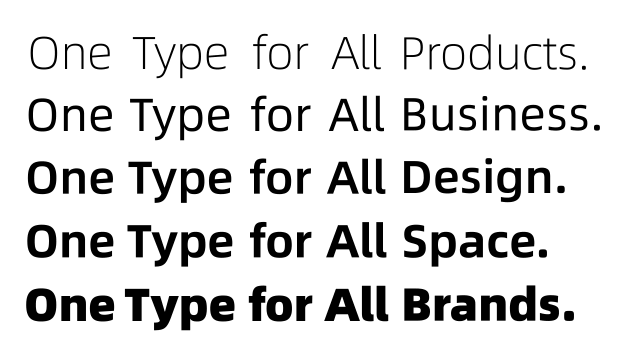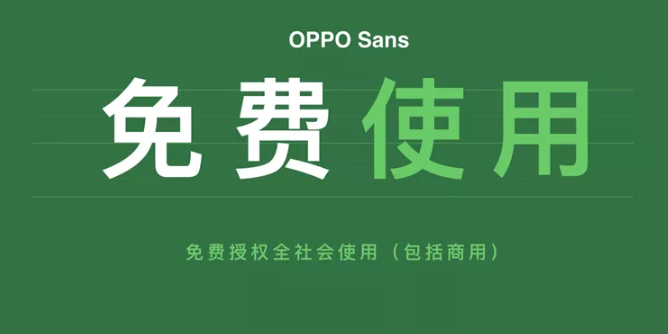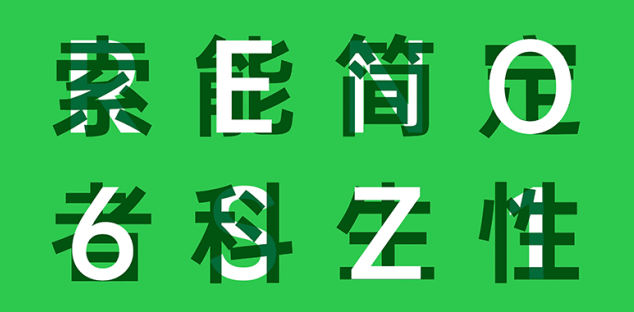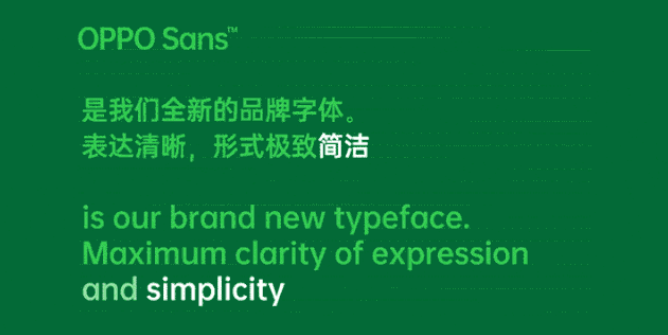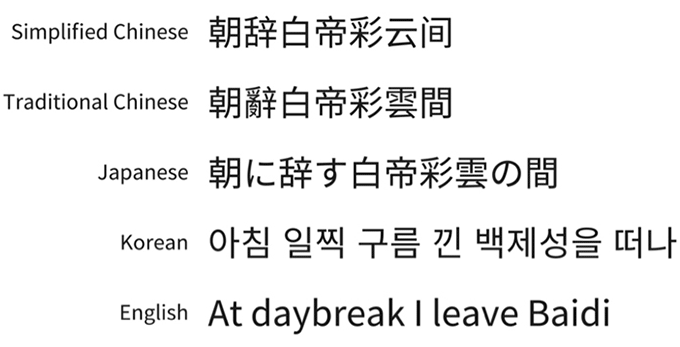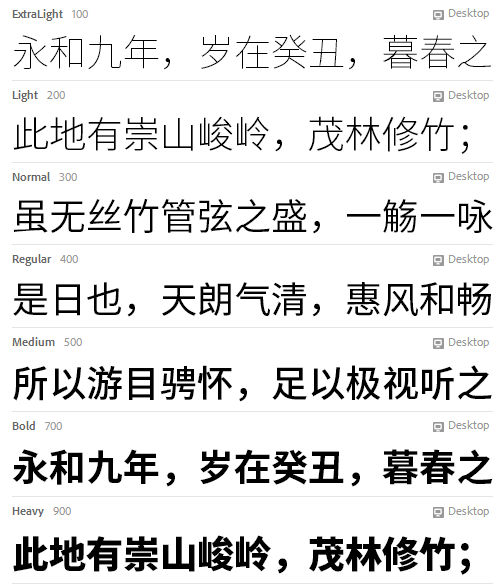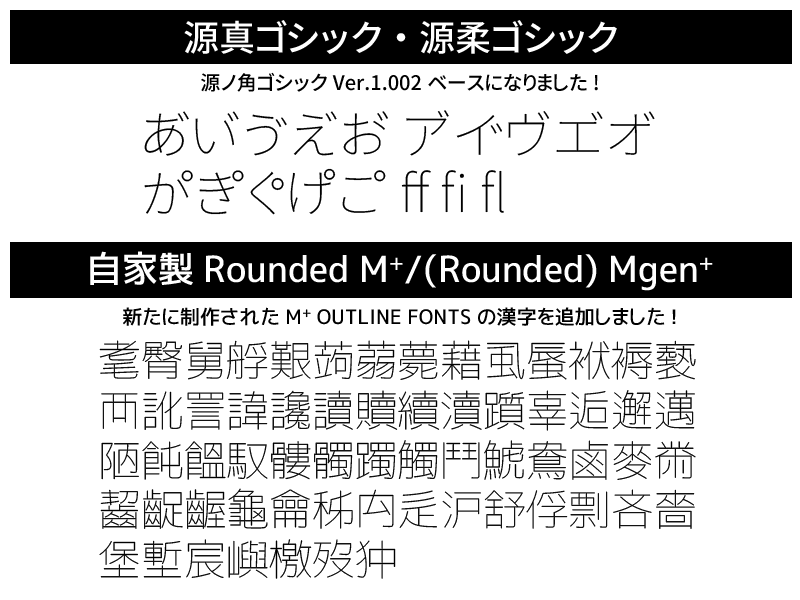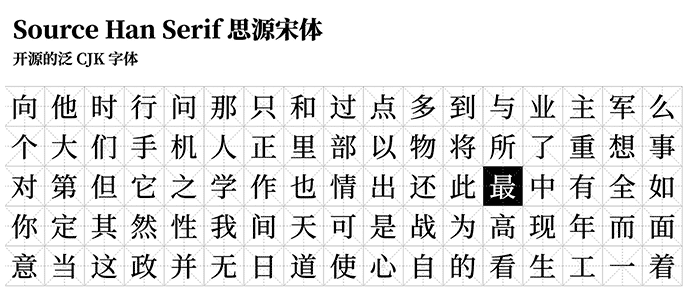
阿里巴巴普惠字体
「阿里巴巴普惠字体」是由阿里巴巴发布的免费可商用字体,包含中文、英文和多种西文。
一共收录 116,895 个全形汉字,几乎涵盖了所有生僻字,并且包含 5 种字重粗细。西文 Alibaba Sans 则共收录有 7,205 个拉丁字母,提供 2 种风格、共 11 种字重,总共覆盖了 172 个语种!
这款字体由著名字体公司蒙纳 Monotype 公司字体总监小林章主导西文字体部分的设计,汉仪字库主创设计师陶一泓主导中文部分的设计。
整套字体设计历时了 10 个月,不仅包含突显企业品牌个性的标题字体,也囊括了更为实用的内文字体,适用于不同场景下的多种应用。
OPPO Sans
由 OPPO 推出的免费可商用「OPPO Sans」字体定位为全球化品牌字体,共覆盖21个国家语言,共11个语种。新字体总共有28874个字符,符合GB18030-2000标准,常用的中文字符都有覆盖。
「OPPO Sans」的中文部分由汉仪字库字体设计完成,西文部分则由美国 Pentagram 五角公司设计,汉仪字库西文项目组协作完成。
「OPPO Sans」采用了全新骨架,中宫自然舒适,结构稳定,字形舒展,视觉重心的提高,让整体造型看起来挺拔优雅,充满生命力。
「OPPO Sans」提供了5种级别字体粗细( Light / Regular / Medium / Bold / Heavy)满足不同场景阅读和设计需求。
思源黑体
「思源黑体」是由 Google 和 Adobe 合作出品的字体,两大巨头共同设计质量肯定高,除了免费可以商用外,还开源了。
「思源黑体」思源黑体整个字体家族的字形数接近50万,整套字体开发过程持续了4年,语言上有简体、繁体、日文、韩文、英文。字体粗细支持7种(ExtraLight、Light、Normal、Regular、Medium、Bold 和 Heavy)。
「思源黑体」设计目标是可以广泛用于多种用途的计算机字体,比如用于手机、平板、或者桌面的用户界面、网页浏览或者电子书阅读等等。SoftGoing发现挺多玩手机美化的用户爱用这款字体进行二次修改。
思源柔黑体/真黑体
「思源柔黑体」「思源真黑体」这两款是上面介绍过的 「思源黑体」修改版本,由日本 自家製フォント工房制作。支持简体中文、繁体中文以及日文三种语言。
「思源柔黑体」一共发布了 3 个版本,分辨是标准版、L、X。它们的区别在于圆角的圆润程度不同,L 圆角最小 (最尖),X 圆角最大 (最圆),而标准版则是介于两者之间。每个版本都有 7 种字重,3种字形样式 (包括等宽字体),大家可以根据喜好选择使用。
「思源真黑体」保留了思源黑体原版的优雅以及高可读性的特色,也是提供了 7 种不同的字重、3种字形样式 (包括等宽字体、比例字体)。格式上转换成 TrueType (TTF) 版,细节上也做了很多的调整与变化,使得整套字体看起来更加锐利清晰,更适用于大量文字阅读显示、代码编程、排版、打印等。
思源宋体
「思源宋体」同样是由 Google 和 Adobe 合作出品的字体,共收录高达 458,745 个字型。
包含简繁中文以及日韩四种汉字写法和 ExtraLight,Light,Regular,Medium,SemiBold,Bold 和 Black 七种粗细字重,可以满足不同的设计需求。
「思源宋体」相比「思源黑体」加入了点、撇、捺、钩等修饰,比较适合文本阅读,如出版小说。